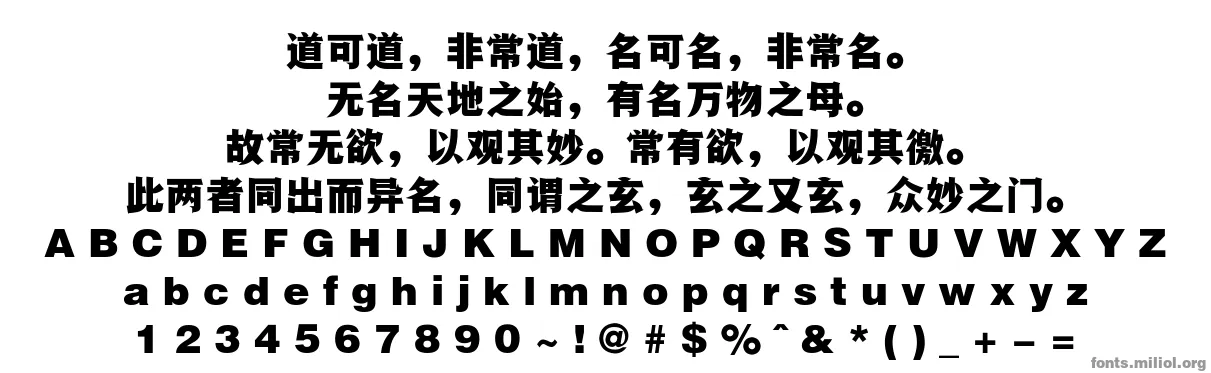
《方正跃进体_GB18030:一款兼具历史感与现代审美的字体》
方正跃进体_GB18030(FZYueJinTi-R-GB18030)是一款充满时代特色的中文印刷字体,其设计灵感源于20世纪中叶的标语美术字,笔触刚劲有力,结构方正稳重,兼具历史厚重感与现代视觉表现力。字体名称中的“跃进”二字,呼应了特定历史时期的审美风格,横平竖直的笔画中透露出鲜明的力量感,适合用于标题、海报、品牌宣传等需要突出视觉冲击力的场景。
作为符合GB18030编码标准的字体,它完整支持简体中文、繁体中文及生僻字符,确保了多场景下的兼容性。其独特的字形设计既保留了传统印刷体的规整,又融入了动态的节奏感,为设计作品增添了一抹怀旧与创新的碰撞。无论是文化主题项目还是商业视觉设计,方正跃进体都能成为传递时代精神的视觉载体。